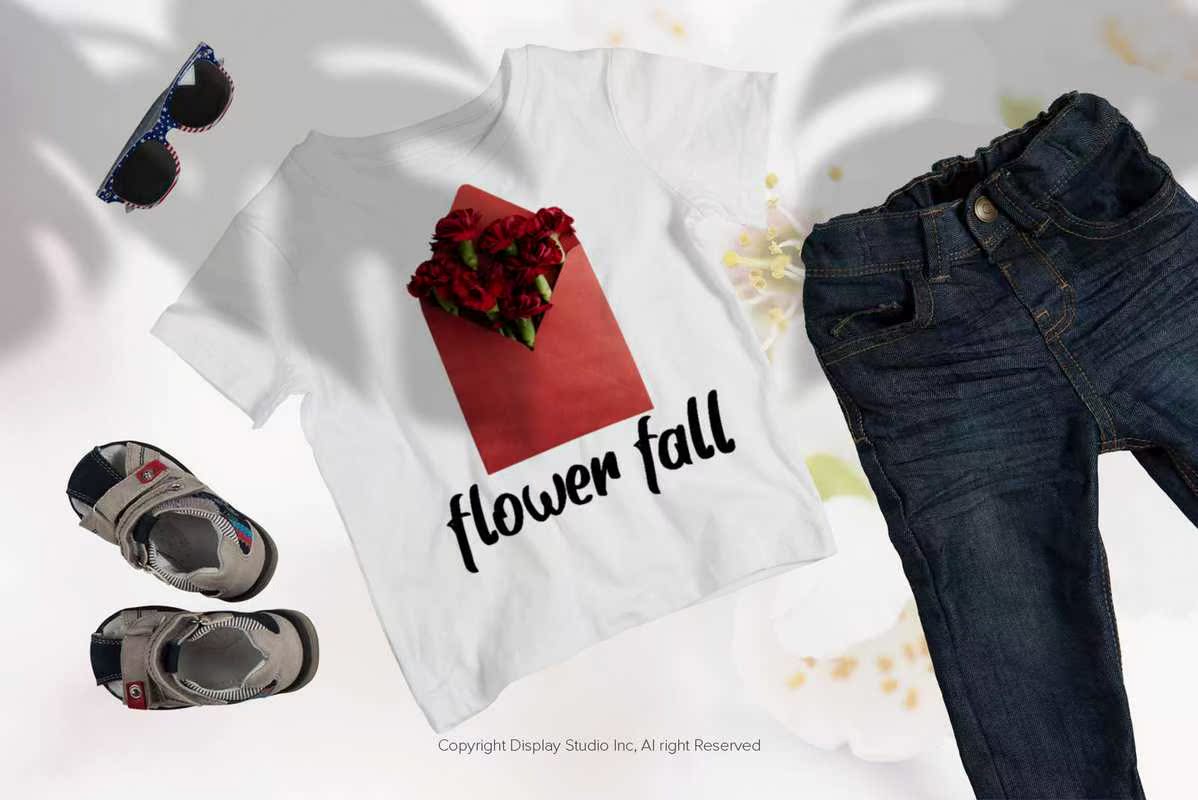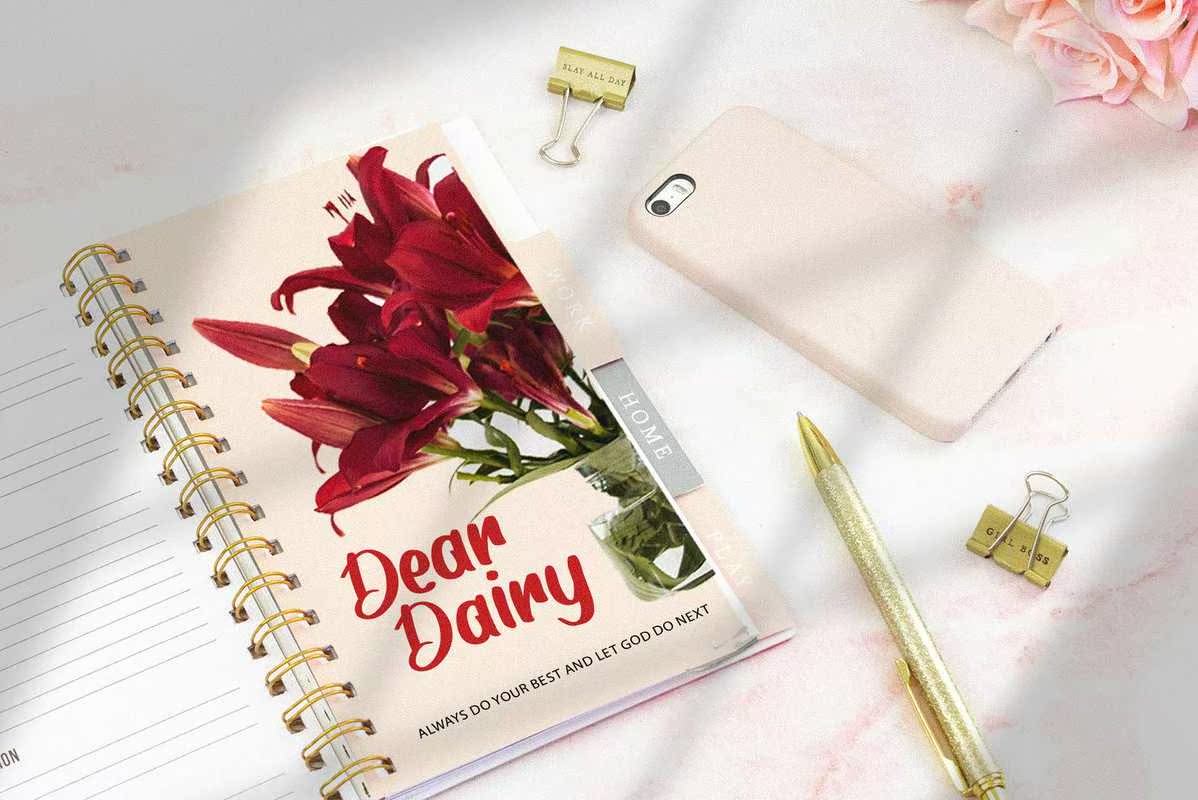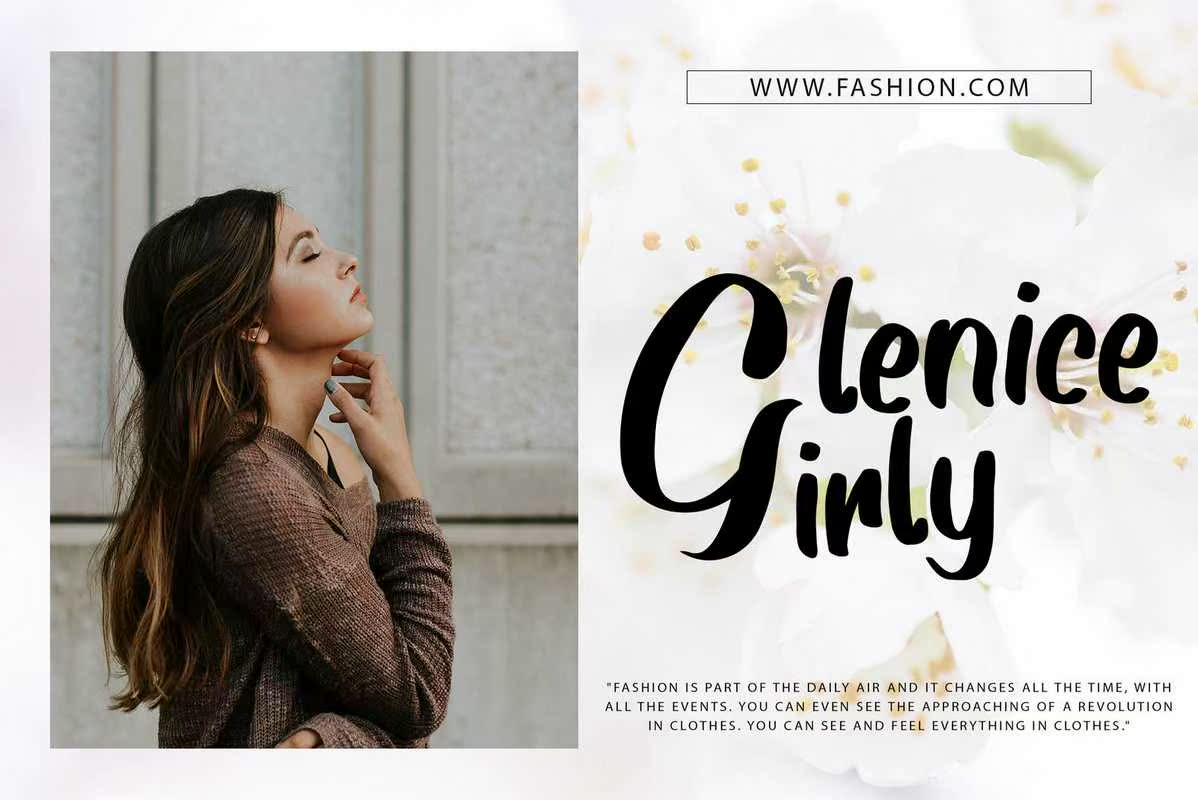
全新和现代风格的Scarlet Children Font。适合您的项目的文字和数字集合非常适合于标识、品牌设计、标识设计、数字刻字艺术、T恤/服装、海报、杂志、标志、广告设计和任何设计需求。全新和现代风格的Scarlet ChildrenFont。适合您的项目的文字和数字集合非常适合于标识,品牌设计、标志设计、数字文字艺术、T恤/服装、海报、杂志、标志、广告设计和任何设计需求。